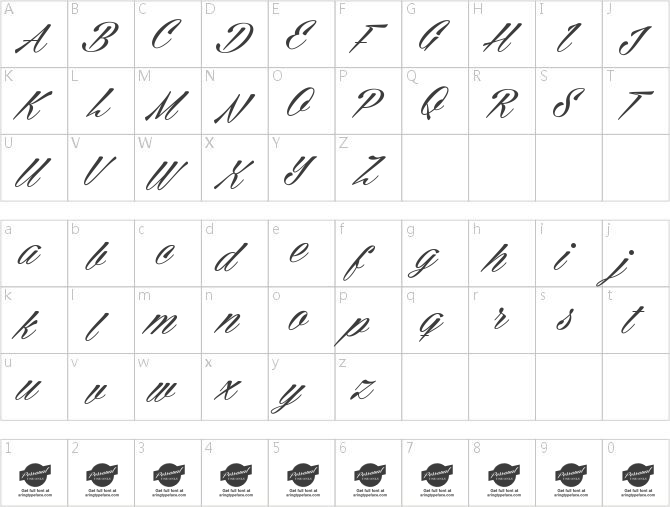
CellosScript_PersonalUse 詳情頁
CellosScript_PersonalUse字體字庫(kù)是一款讓人賞心悅目、百看不厭的英文字體,適合各類廣告和產(chǎn)品包裝設(shè)計(jì)應(yīng)用,字體大小0.24MB,格式為ttf字體,上傳用戶是快霸中國(guó),作者/版權(quán)方為未知